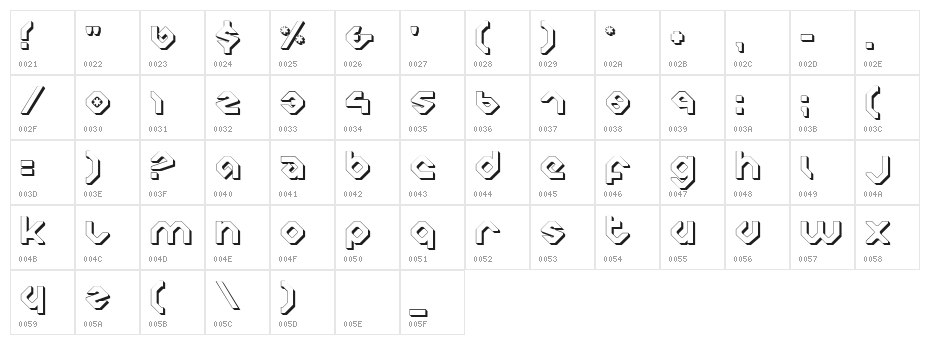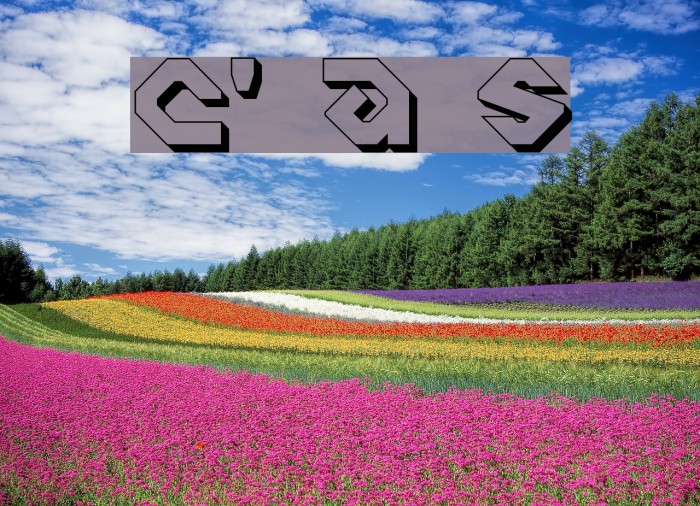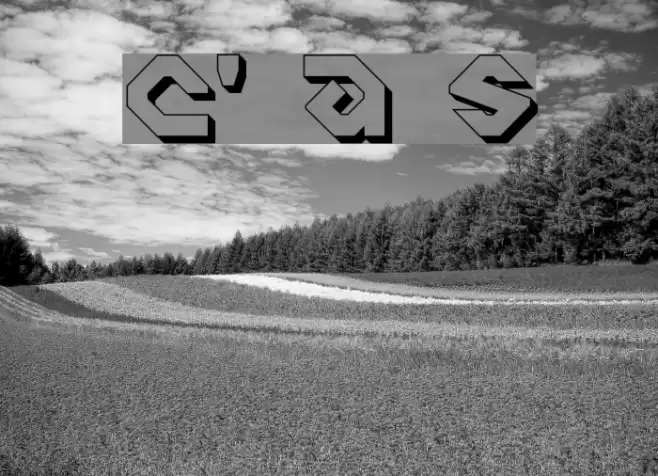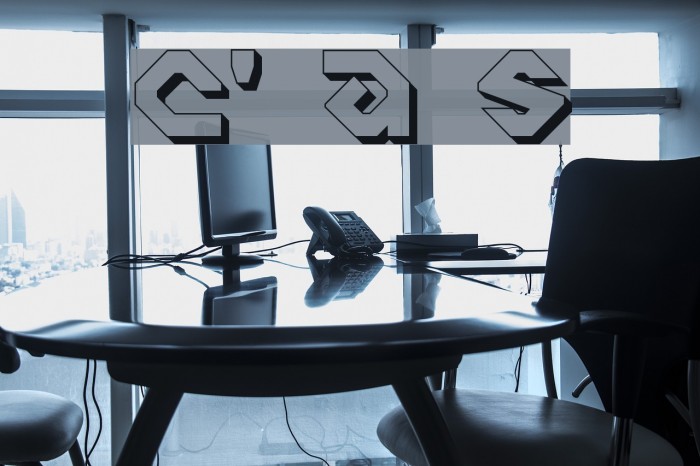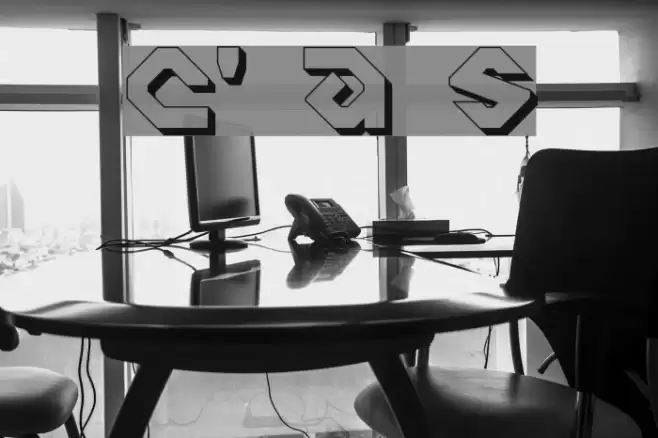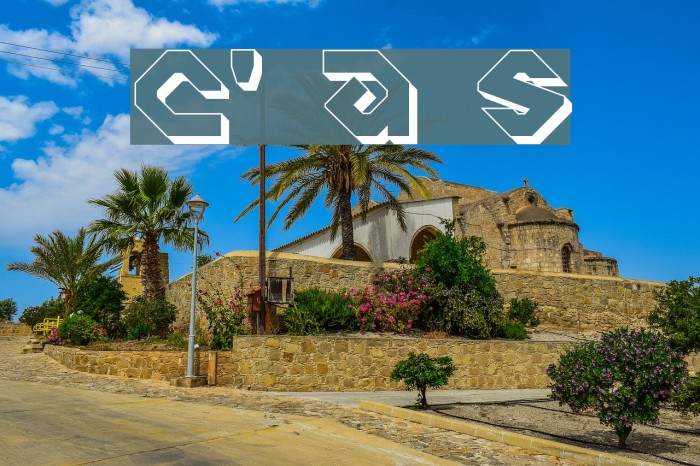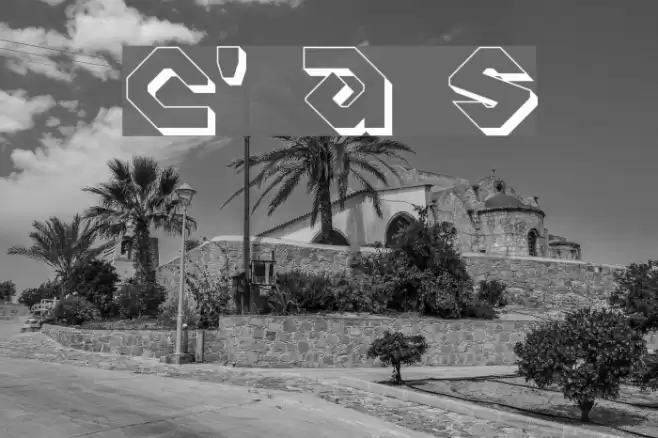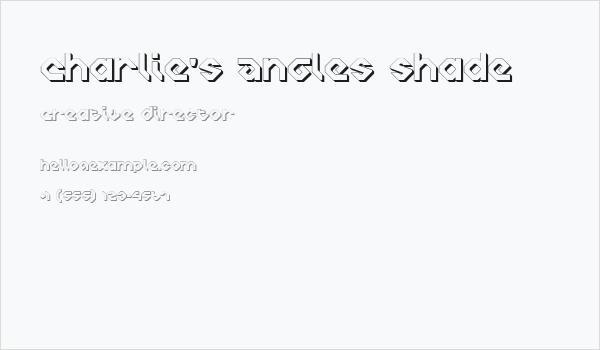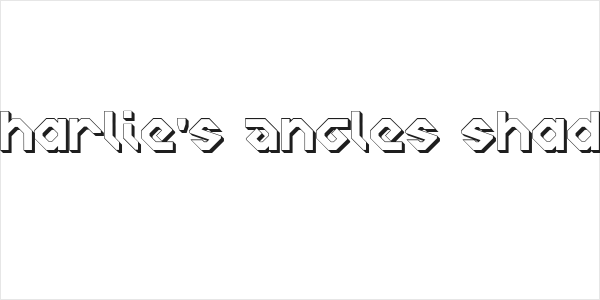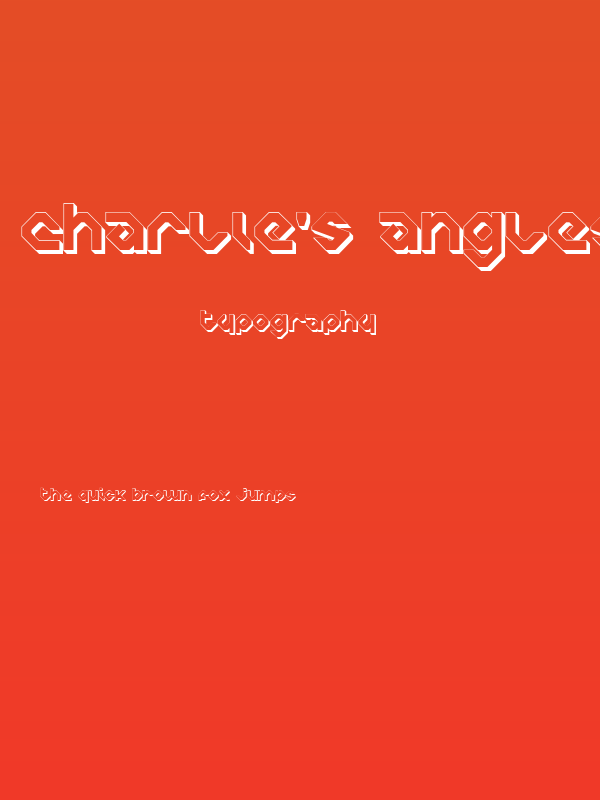
Charlie's Angles Shade Font
| Projets proposés | Ideal for posters, logos, video game graphics, and any project requiring a bold, modern typeface. |
Charlie's Angles Shade